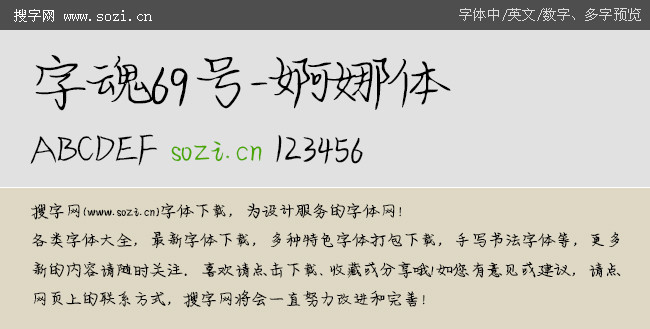
字魂69號-婀娜體
搜字網(wǎng)提供一款字魂69號-婀娜體中文字體下載,該字體是一款硬筆手寫字體,該字體包含9399個(gè)中文、字母、 符號和數(shù)字,具有優(yōu)雅、浪漫、溫柔、中國風(fēng)、古典 的風(fēng)格,可以滿足您設(shè)計(jì)上的各種需求,該字體主要用于企業(yè)店鋪、廣告、影視傳媒、新媒體、、活動(dòng)、美食餐飲 等場景。